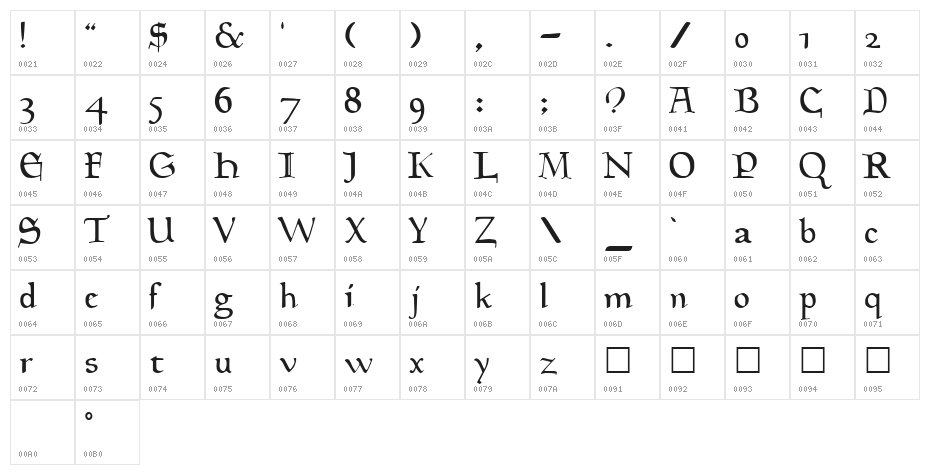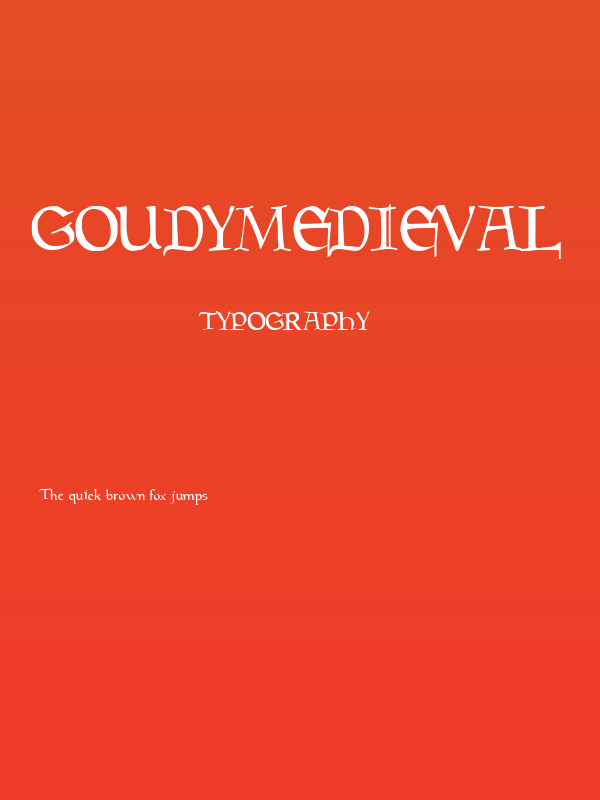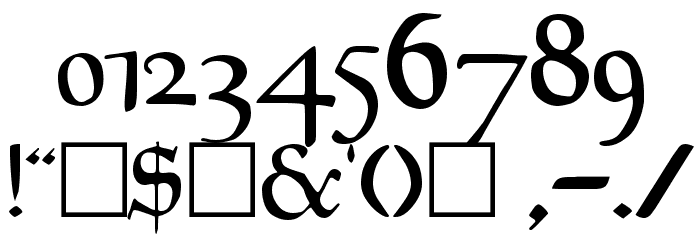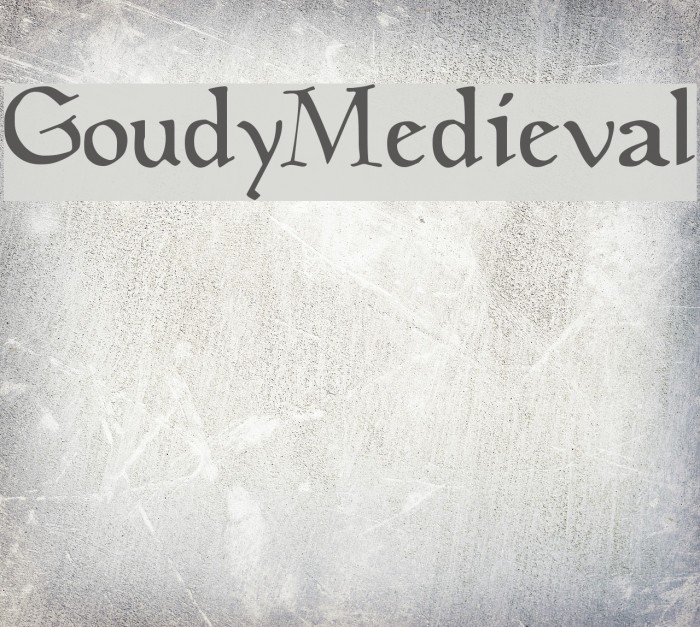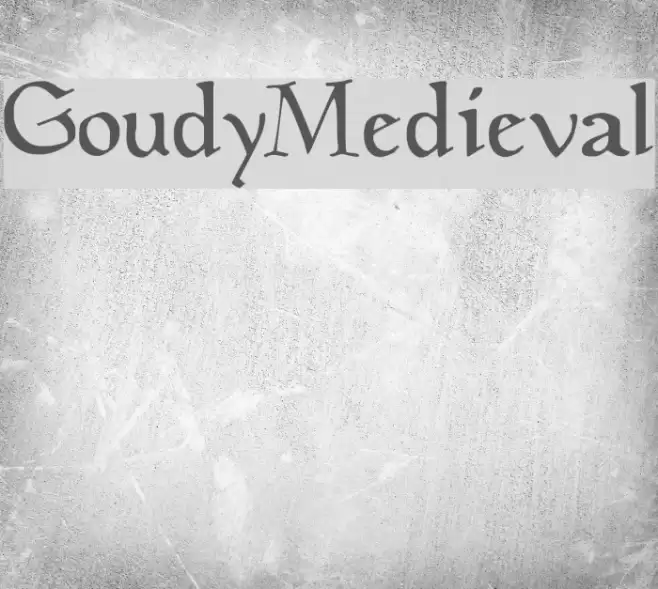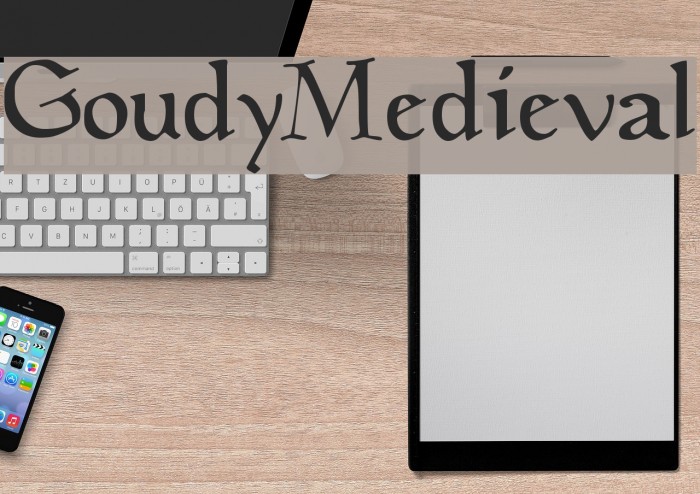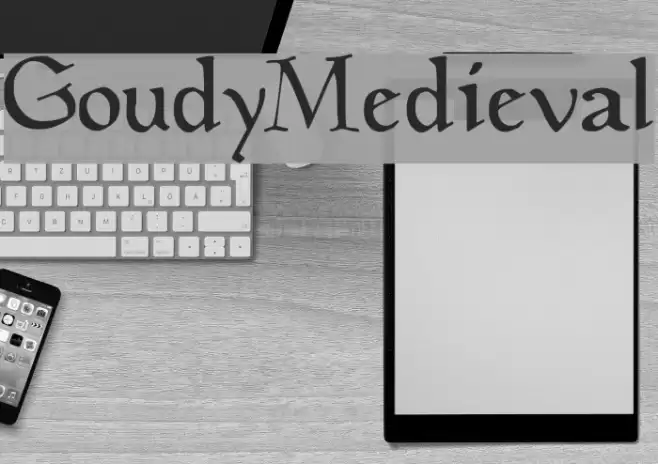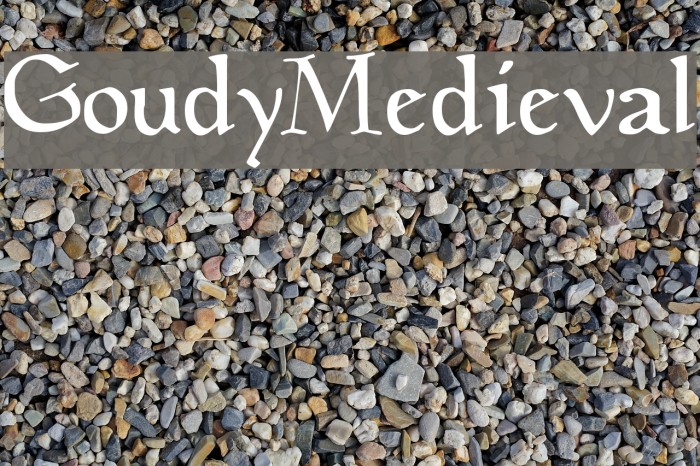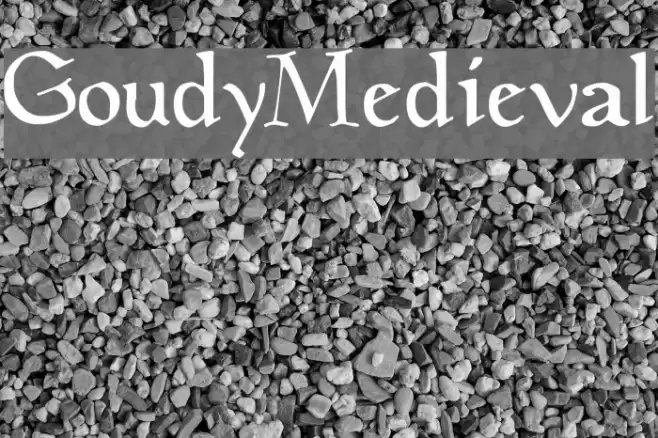
GoudyMedieval Font
Fonts by Altsys Metamorphosis
| Caso d'uso | Headlines, Logos, Decorative text |
| Progetti proposti | Perfect for book covers, historical documents, themed event invitations, and branding that requires a medieval or vintage touch. |